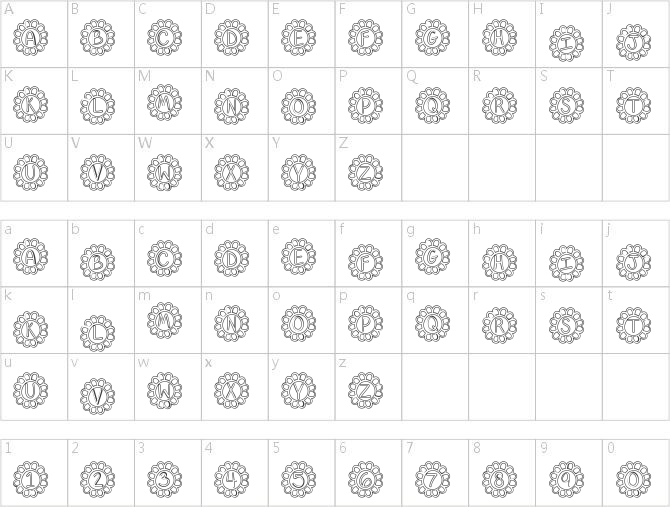
Flower Power Hollow 詳情頁(yè)
Flower Power Hollow字體字庫(kù)是一款讓人賞心悅目、百看不厭的英文字體,適合各類(lèi)廣告和產(chǎn)品包裝設(shè)計(jì)應(yīng)用,字體大小0.13MB,格式為ttf字體,上傳用戶(hù)是/zyj【GF】,作者/版權(quán)方為未知